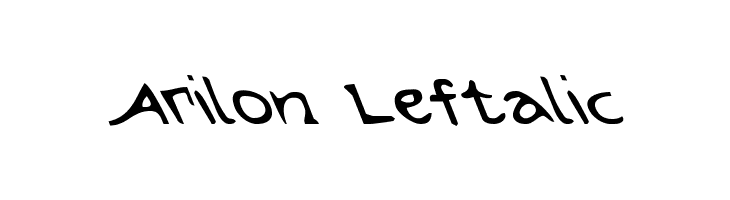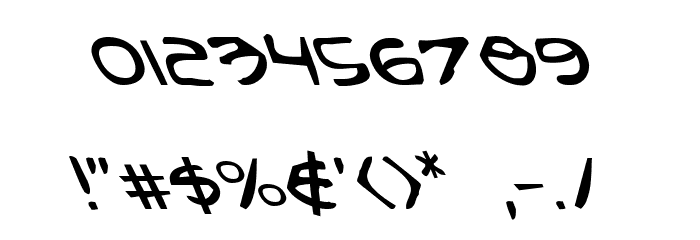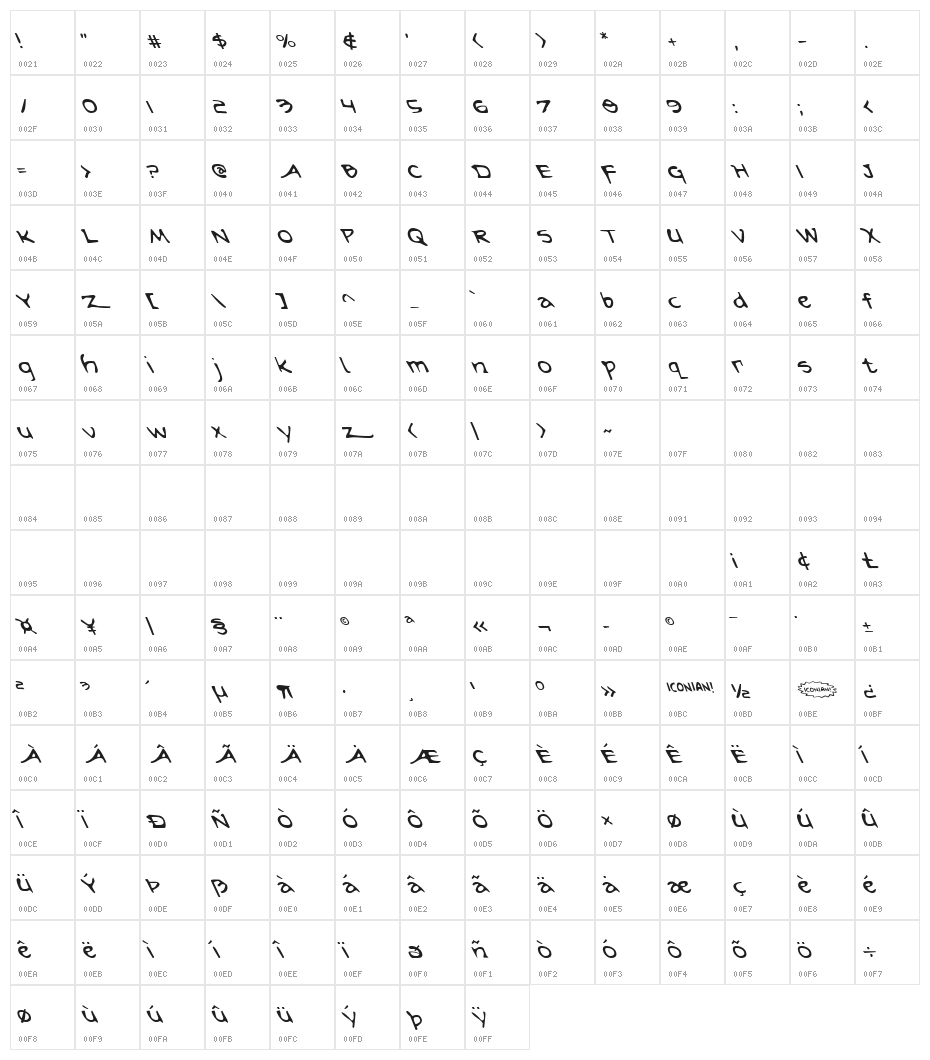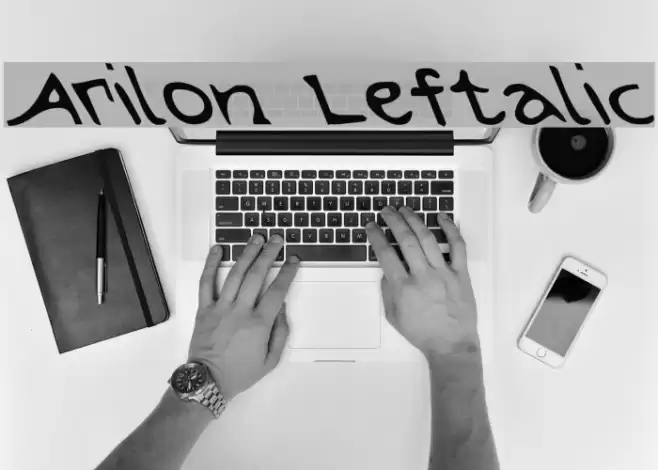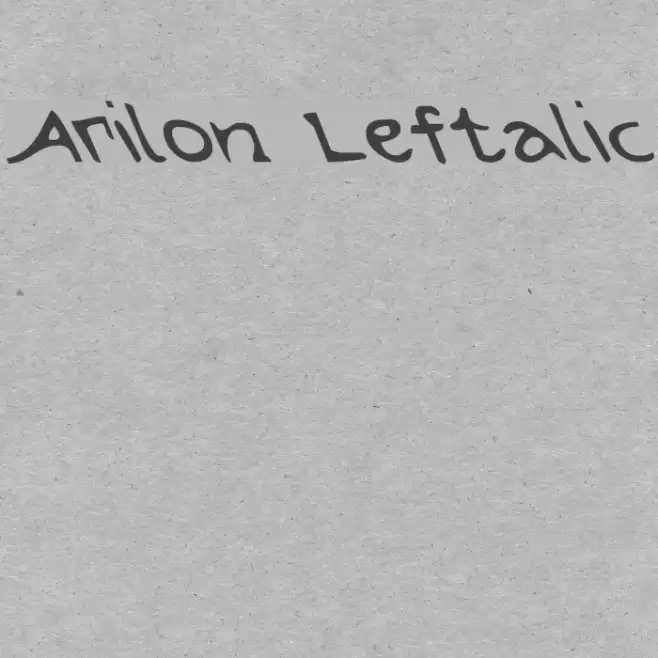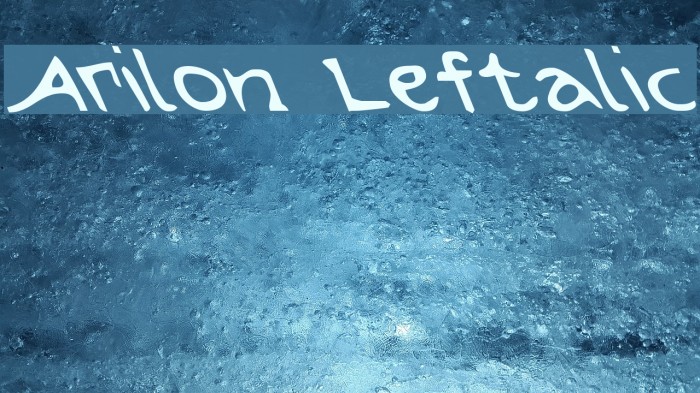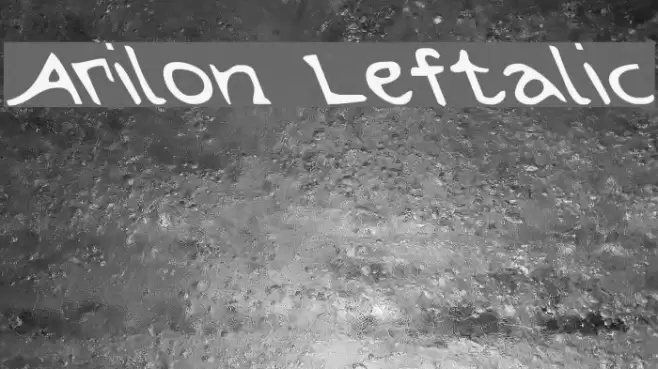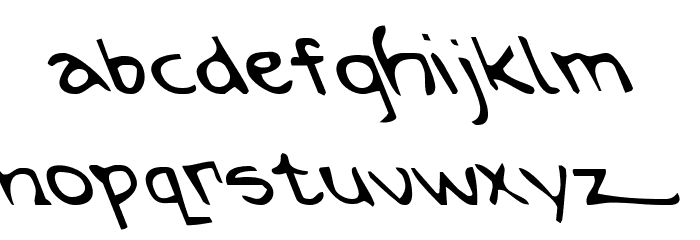
Arilon Leftalic Font
NomArilon Leftalic
PoidsItalic
CatégoriesHandwritten
GrasYes
ItaliqueYes
LargeurNormal
Espacement des caractèresMonospaced
ContrasteMedium
Style généralModern, Decorative
Cas d'utilisationHeadlines, Logos, Artistic projects
Projets proposésPerfect for creative projects such as posters, album covers, branding, and artistic designs that require a bold and unique typeface.